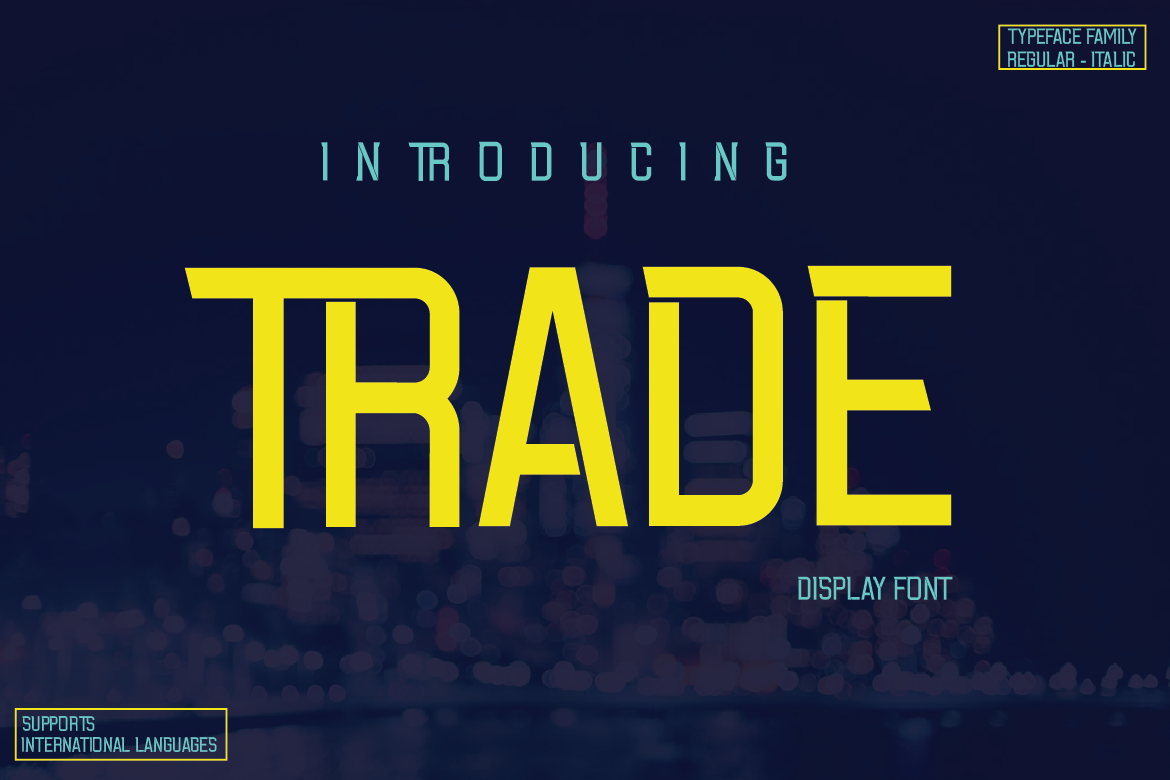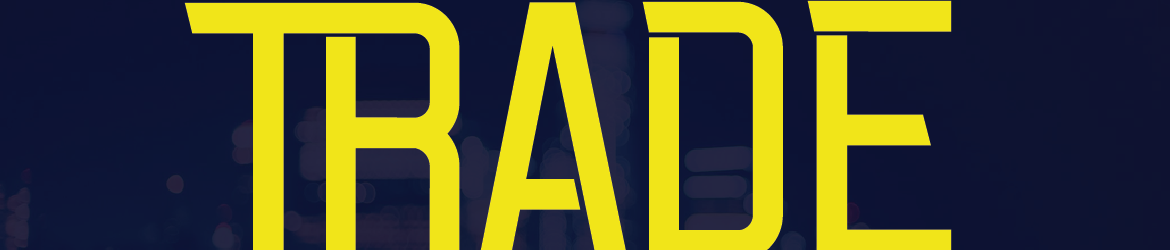
Esta é uma fonte de exibição alegre e bold. Desenvolvida com habilidade para tornar suas criações parecerem fora deste mundo, esta font irá brilhar em uma variedade de ideias e projetos. Ideal para adicionar um toque notável e criativo aos teus designs digitais. Antônio Sepertiawan é o designer da fonte ‘Trade Font’, que se destaca por sua elegância cuidadosamente pensada, tornando-a perfeita tanto para aplicativos gráficos complexos quanto para projetos simples. Sua textura única e personalidade vibrante garantem que você nunca fique estagnado na mesmice. Não importa o projeto que você está criando — seja uma identidade visual moderna ou um layout de newsletter atraente, ‘Trade Font’ irá transformar suas ideias em algo único e memorável. Com sua grande variedade de opções, é fácil incorporar essa fonte no seu design para destacar os detalhes mais importantes, garantindo que seu trabalho seja lembrado por muitos anos. Com ‘Trade Font’, você pode criar designs que se destacam, oferecendo uma alternativa única aos outros projetos existentes. Suavizando o brilho e a audácia desta fonte, é ideal para ambientes de design moderno, garantindo um visual inovador e memorável. Seja em um design minimalista ou em um design extravagante, ‘Trade Font’ sempre manterá seu estilo pessoal vibrante, proporcionando uma experiência única e inspiradora para quem a usa.